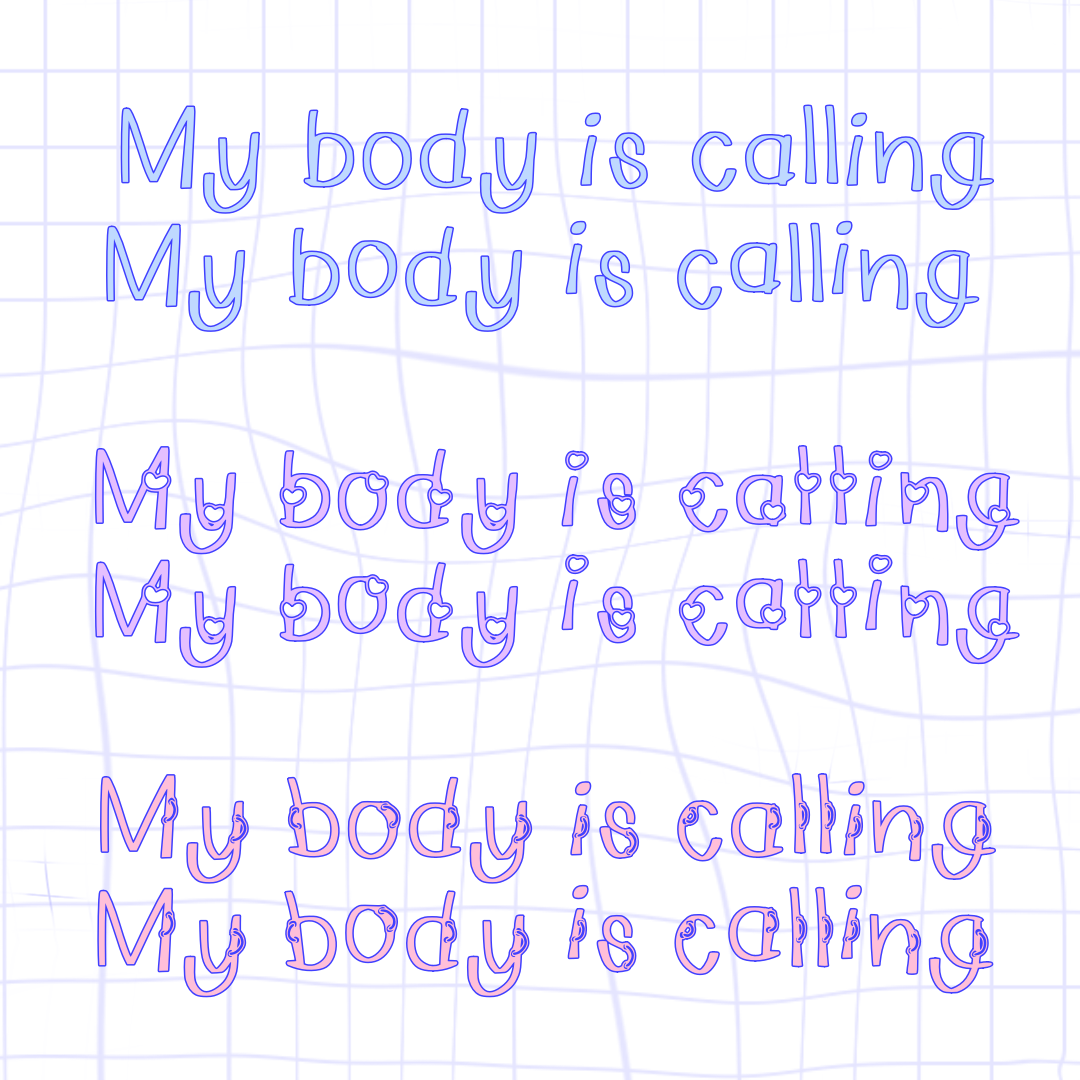
นูร่าอนาย่า (Nura Anaya)
ฟอนต์ลายมือตัวบาง มีความวาไรตี้มาก มีด้วยกันสามเวอร์ชั่น คือ ธรรมดา หัวใจ และมีโซ่่  นูร่าราดาเปิดให้ใช้ฟรีส่วนตัวทุกเวอร์ชั่นนะคะ